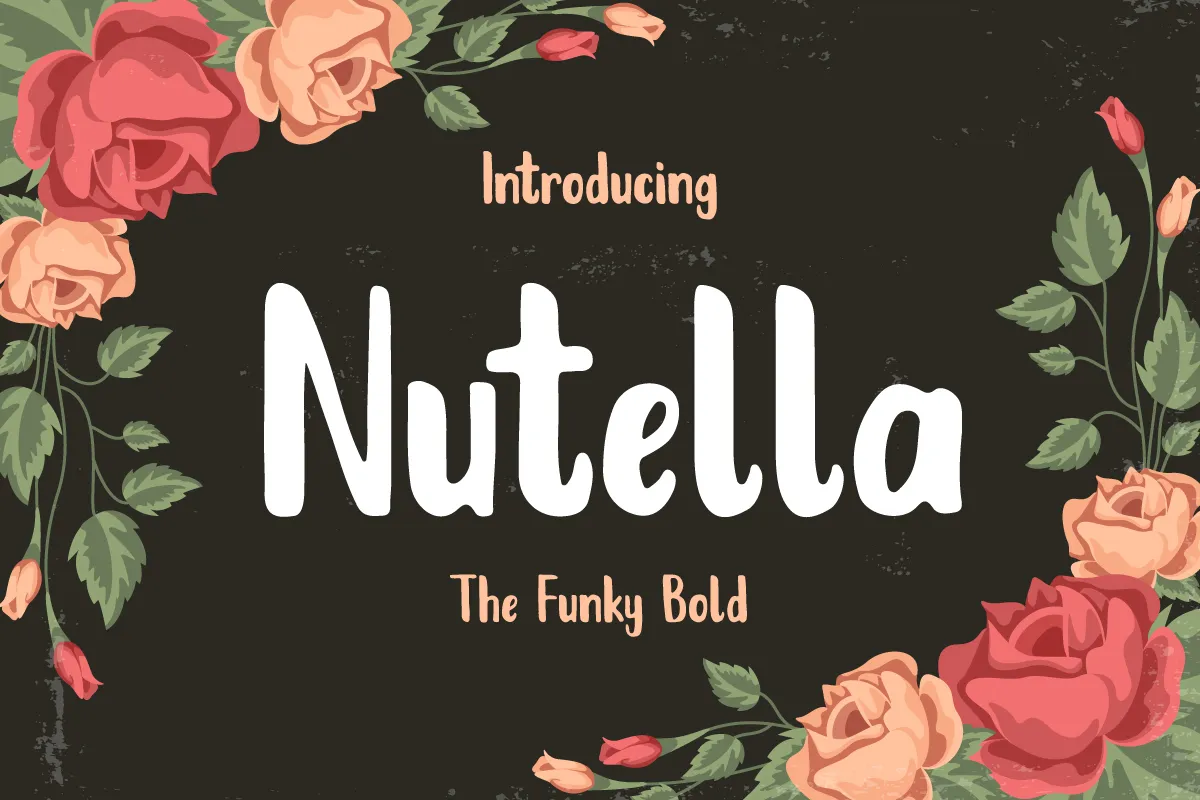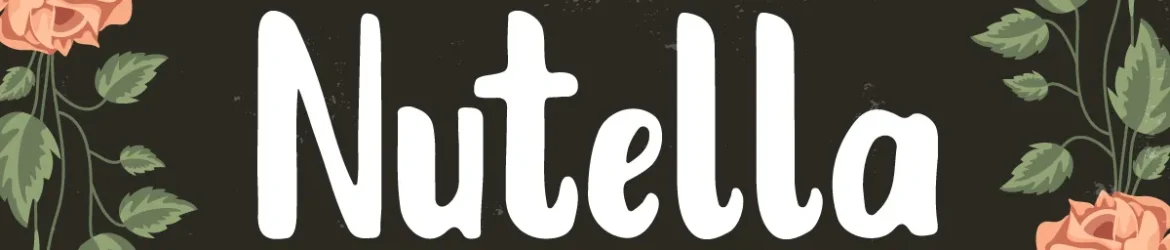
Introduzimos Nutella Font! Esta é uma font premium criada por Kang1993, disponível para download grátis hoje no Creative fabrica. Kang1993 transformou a Nutella em um tipo de fonte com aspecto de canetinha contemporânea. Foi pintado à mão e digitalmente cuidadosamente perfeito. A fonte adquire um estilo elegante e levemente divertido, que se adapta bem para diferentes tipos de projetos. Nutella é uma fonte ideal tanto para o design gráfico quanto para a criação de identidades digitais. Com sua aparência moderna e sua forma brilhante, ela dá um toque único aos seus trabalhos. Para quem procura uma fonte que combine estilos diferentes, essa pode ser a escolha perfeita. Seja em um design de aplicativos ou até mesmo para o seu site pessoal, Nutella irá deixar sua obra ainda mais especial e único.